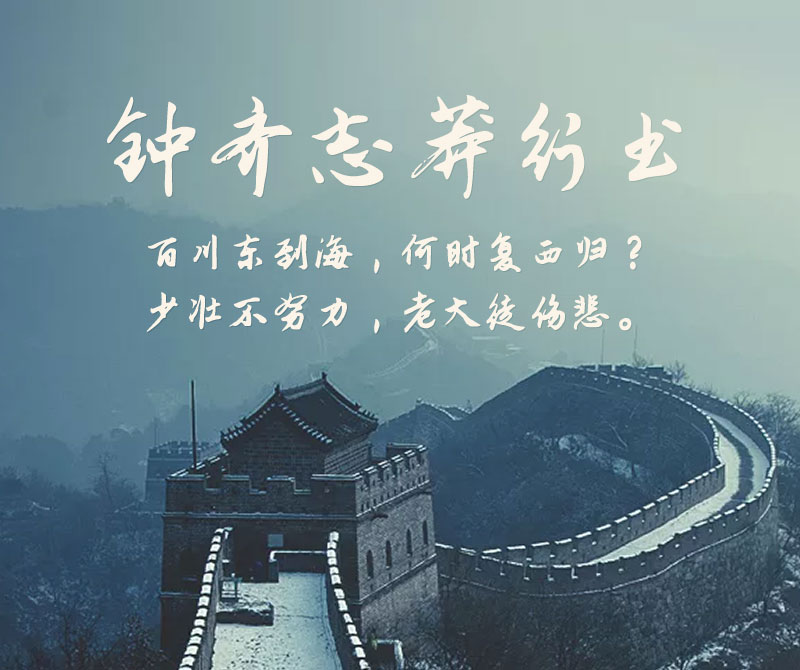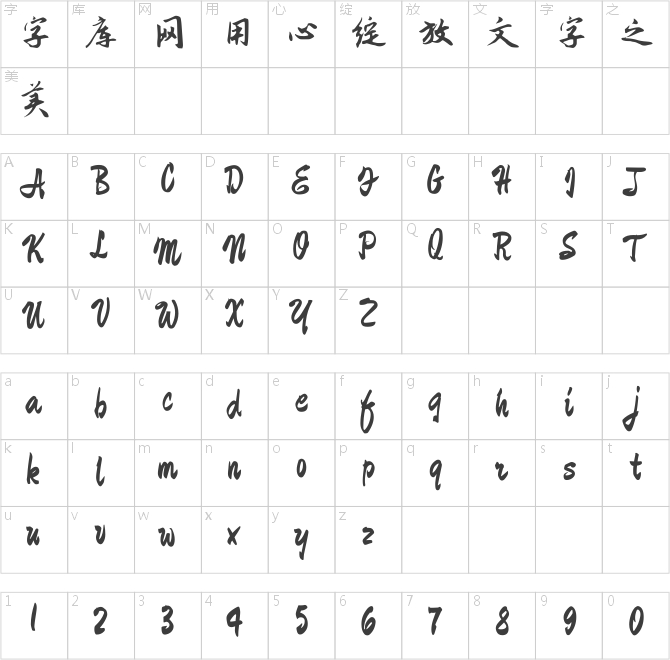
钟齐志莽行书 详情页
钟齐志莽行书
钟齐志莽行书一款笔画干练的古风书法字体,软件显示名称(Zhi Mang Xing)谷歌开源字体项目里面其中一款中文字体。
钟齐志莽行书字体字库是一款让人赏心悦目、百看不厌的中文字体,适合各类广告和产品包装设计应用,字体大小3.88MB,格式为ttf字体,上传用户是星期一,作者/版权方为钟齐字库